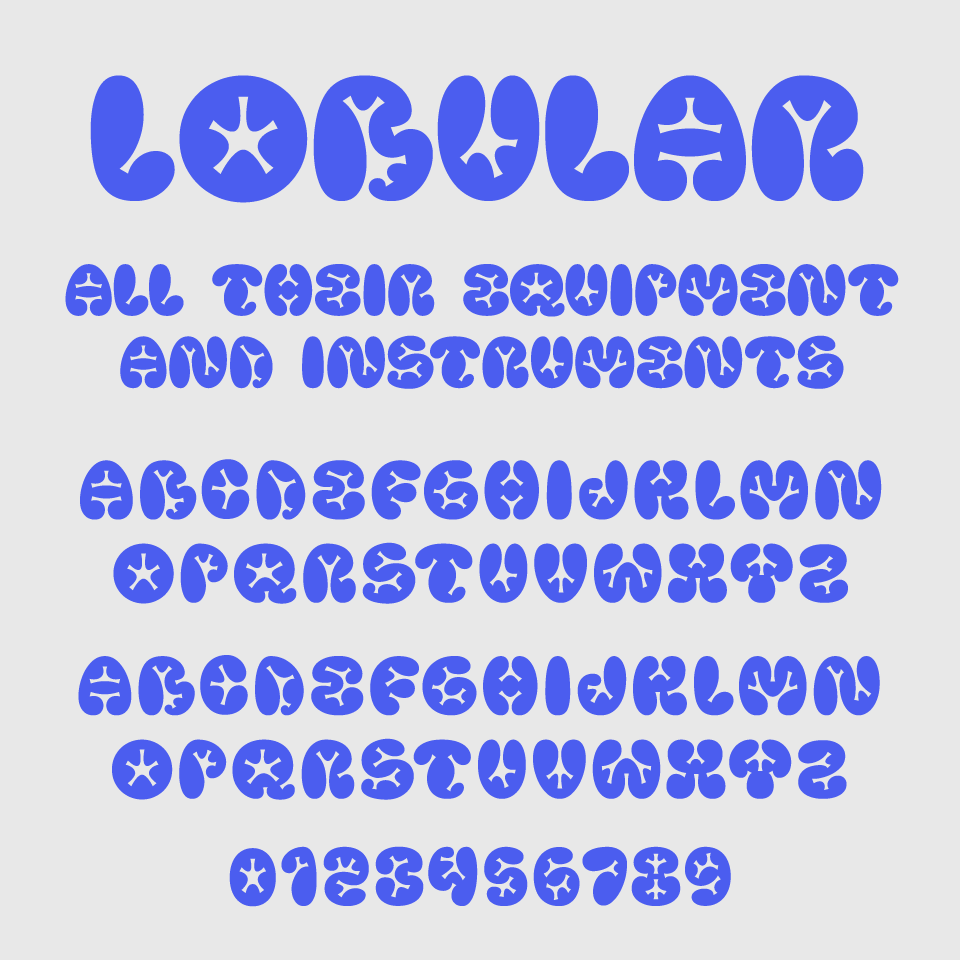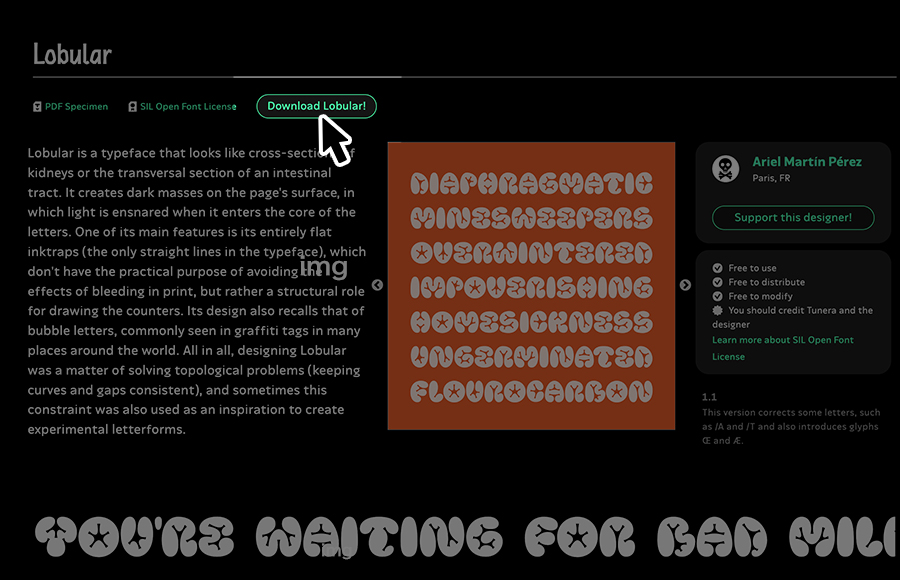
Lobularフォントは、バブルのような膨らみと植物のような装飾が融合した、とても個性的なディスプレイフォントです。まるでグミやキャンディのような可愛らしさがあるデザインです。
文字一つひとつにキャラクターがあり、視線を惹きつける力が抜群です。インパクトが強く、使用場面は限定されますが、可愛らしいフォルムは、子供向けのロゴやグッズ展開、ポップカルチャーをテーマにしたイベントのタイトルなどにはぴったりです。
収録文字は、大文字/数字/記号の収録となっています。